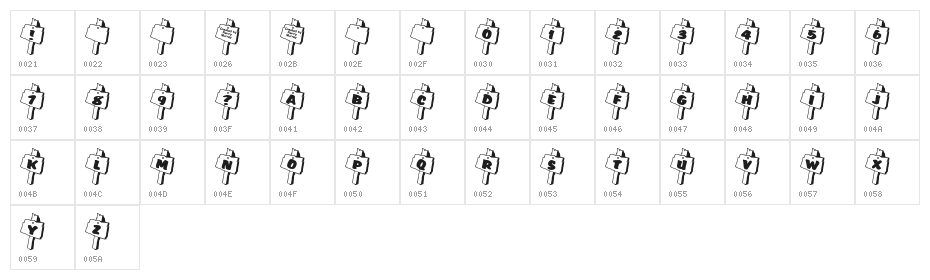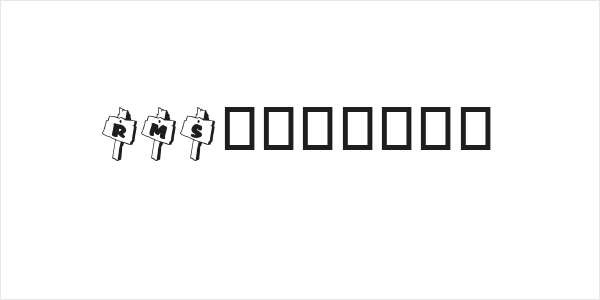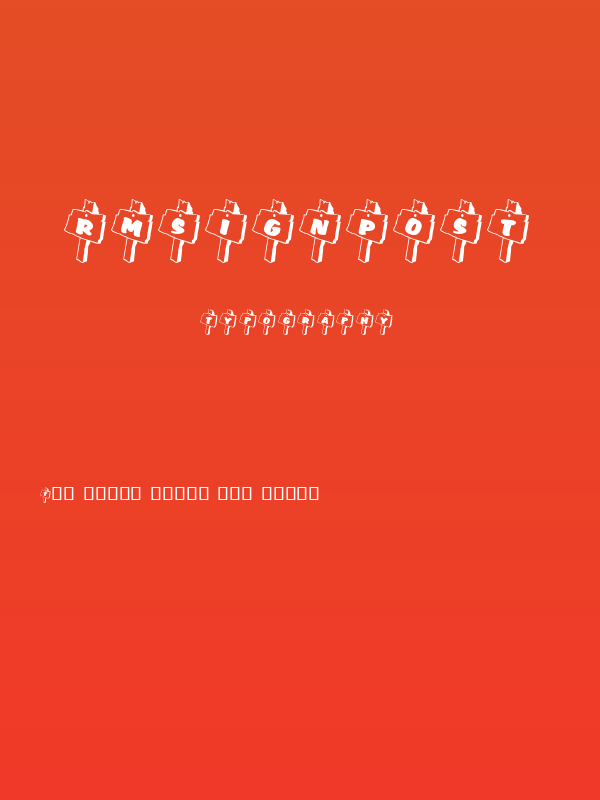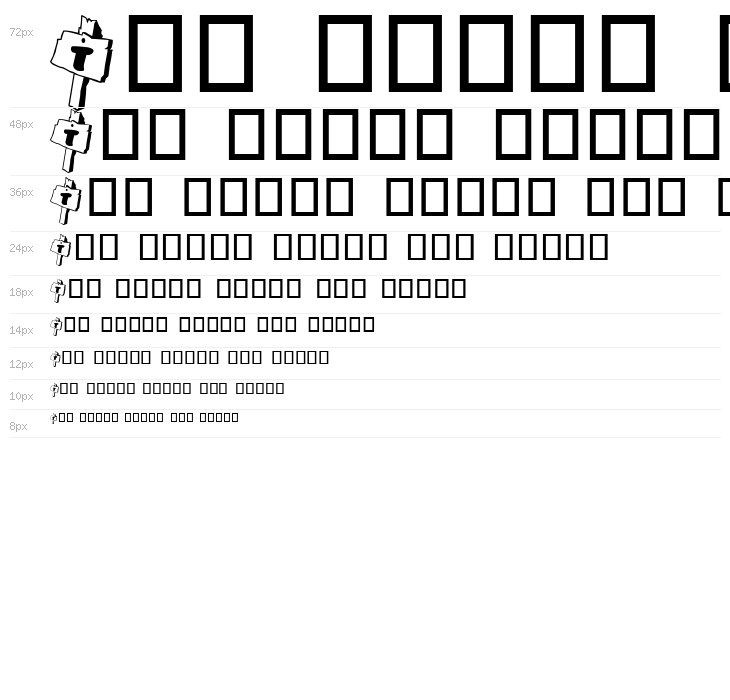
RMSignpost Font
| Progetti proposti | Ideal for children's books, playful branding, event posters, and any project needing a fun, eye-catching design. |